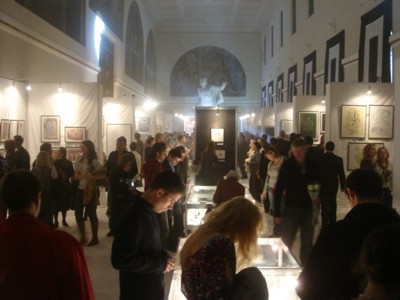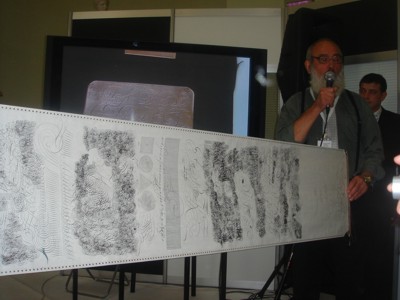
INTERNATIONAL EXHIBITION OF CALLIGRAPHY
ST. PETERSBURG 2008
| Die weltweit bisher größte Ausstellung der Kalligrafie aus Ost und West, aus Nord und Süd, fand vom 16. bis 22. September 2008 in St. Petersburg statt. Teilnehmer aus Russland, Belarus, der Ukraine, China, Japan, Taiwan, Indien, Israel, Jordanien, Armenien, Persien, Syrien, Tatarstan, Südamerika, Australien, den USA, der Türkei, Island, Finnland, Norwegen, Belgien, den Niederlanden, Italien, Frankreich und Deutschland fanden erstmals ein Forum, ihre Arbeiten einem großen Publikum zu präsentieren. Innerhalb von sechs Tagen kamen über 25.000 Besucher, um sich die Ausstellung anzusehen! Teilweise haben die Besucher weite Reisen auf sich genommen, um diesem kulturellen Ereignis beizuwohnen. Eine Licht- und Lasershow sowie klassische Musik umrahmten die hervorragend präsentierte Ausstellung. In zwei großen Sälen der Kunsthochschule Ilja Repin aus der Zeit der Renaissance, die mit Wandgemälden und gigantischen Skulpturen dieser Zeit ausgestattet waren, wurden einerseits der russische und lateinische Schriftenkreis gezeigt, andererseits, im gegenüberliegenden symmetrisch angeordneten Saal der hebräische, ostasiatische, indische sowie ebenfalls kyrillische Schriftenkreis. |
Die ganze erste
Etage dieses Gebäudes, das "Repin St. Petersburg State Academic
Institute of Painting,
Sculpture and Architecture", war eine Woche
lang Schauplatz der größten jemals gezeigten Kalligrafie-Ausstellung.
10 Fernseh- und Rundfunkteams filmten und fotografierten rund um die Uhr,
machten Interviews und Life-Übertragungen.
| Riesige Rosenbuketts schmückten die Eingangstreppe der Ausstellung, und zwei Klaviere spielten den ganzen Tag automatisch mit elektronisch gesteuerten Tasten. In der Ausstellung waren nicht nur die Arbeiten der über 60 Teilnehmer aus allen Kontinenten präsentiert, sondern auch ein großer Überblick über Schreibwerkzeuge, Literatur zur Kalligrafie und Schriftkultur, Schrift in der Anwendung auf Tellern, Kacheln oder aus Metall oder in Künstler- und Miniaturbüchern. Ein eigener Teil der Ausstellung zeigte historische russische Schriftdokumente aus verschiedenen Jahrhunderten, byzantinische und orthodoxe Texte und Schriften sowie auch einen Originalbrief Katharina der Großen. Eine Ausstellung von Studenten und ein Schreib-Wettbewerb für Kinder ergänzte das Ausstellungsprogramm. |
Jeden Tag präsentierten sich die Ausstellungsräume so voll wie auf diesen Fotos.
Pavel Semchenko aus Minsk (Weißrussland), ein bekannter
Schriftkünstler
in seinem Land und darüber hinaus, präsentierte seine Arbeit, so
auch eine anlässlich
seines diesjährigen 70. Geburtstags gestaltete
ca. 10 m lange Schriftrolle.
Avraham Hersh-Borshevsky
aus Jerusalem demonstrierte zur Eröffnungsveranstaltung neben
Prof. Petr
Chobitko, Prof. Chen Wenfu (China), Prof. Pavel Semchenko (Minsk) und Hans
Maierhofer (Regensburg).
Dr. Nassar Mansour aus Amman (Jordanien) hielt einen
exzellenten Vortrag über die
arabische Schriftkultur und die Herstellung
der Schreibwerkzeuge.
...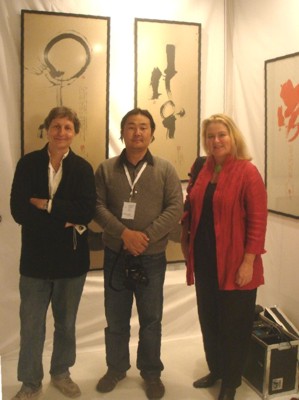
Chen Fong-Shean
aus Taiwan demonstrierte nicht nur auf höchstem Niveau chinesische Schriftkunst,
sondern zeigte auch mikroskopisch kleine Kalligrafien auf Skulpturen und in
winzigen Büchern.
Er ist Miniaturmaler und besitzt in Taiwan ein Museum
für Miniaturmalerei.
Treffen der
Kulturen: Izzy Pludwinsky aus Jerusalem (u.a. Mitarbeiter an der St. Johns
Bible),
Ganzorig Aleyksander aus Ulan Bator (Mongolei) und Katharina Pieper
vor den energiegeladenen Arbeiten von Ganzorig.
Am letzten Tag
der Ausstellung präsentierten sich noch einmal alle Organisatoren der
Ausstellung
und des Kongresses, und der Chef und Hauptinitiator des Ereignisses,
Mr. Alexej Shaburov (rechts im Bild)
ließ sich gerne feiern. Im Hintergrund
sieht man die große Wand, die Andrea und Volker Wunderlich aus Goldkronach
bei Bayreuth während drei Ausstellungstagen vor Ort gestaltet haben.
Ein Publikumsmagnet!
So wurden die
Arbeiten der Aussteller einem Publikum präsentiert, das insbesondere
aus jungen Leuten,
Kindern und Schulklassen sowie aus Besuchern aus allen
Bevölkerungsschichten bestand. Neben allen Arbeiten
hingen Lupen, damit
man sich die teils feine Kalligrafie - wie hier rechts die Englische Schreibschrift
von Jean Larcher - betrachten konnte. Links und auf dem rechten Bild links
die Werke von Katharina Pieper.
...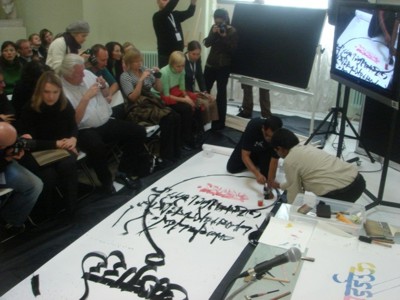
Jean Larcher erklärt jungen Interessierten seine Arbeit. An der rechten Wand Arbeiten von Prof. Werner Schneider.
Achyut Palav
aus Bombay demonstrierte auf einer große Schriftrolle vor allen Zuschauern.
Sein Kollege Manohar Desai unterstützte ihn bei seinem Vortrag über
die Vielfalt der indischen Schrift.
Achyut und Katharina sind seit 22 Jahren
befreundet.
Insgesamt hielten
ca. 25 Kalligrafen, Professoren und Wissenschaftler aus aller Welt Vorträge
und
demonstrierten während der gesamten Zeit der Ausstellung von morgens
bis zum Nachmittag.
So erfuhr man viel über die unterschiedlichen Schriftenkreise
und sah unterschiedliche Methoden
der Demonstration und Präsentation.
Hier zeigt Katharina Pieper, die im Duett mit Jean Larcher "zu vier Händen"
ein Leporello gestaltete, wie man auch mit einfachen Mitteln wie einem Balsaholz
Schrift schreiben kann.
Rechts: eine Arbeit von Leonid Pronenko (Krasnodar).
...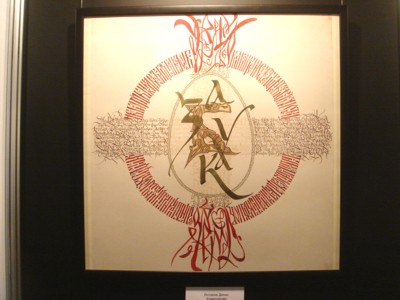
Gunnlaugur SE
Briem (Island/San Francisco) zeigte, dass Schrift auch am Computer höchstes
Niveau erreichen kann.
Rechts eine Arbeit von Olga Varlamova aus der Studentenklasse von Prof. Petr
Chobitko (St. Petersburg).
...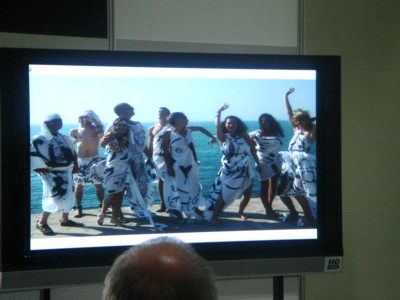
Genady Matsur,
Buchgestalter und Kalligraf aus Minsk und Student von Prof. Pavel Semchenko,
zeigte expressive großformatige Werke. Rechts; Prof. Evgeny Dobrovinsky
zeigte auf seinem Vortrag,
dass Kalligrafie auch am Körper getragen werden
kann.